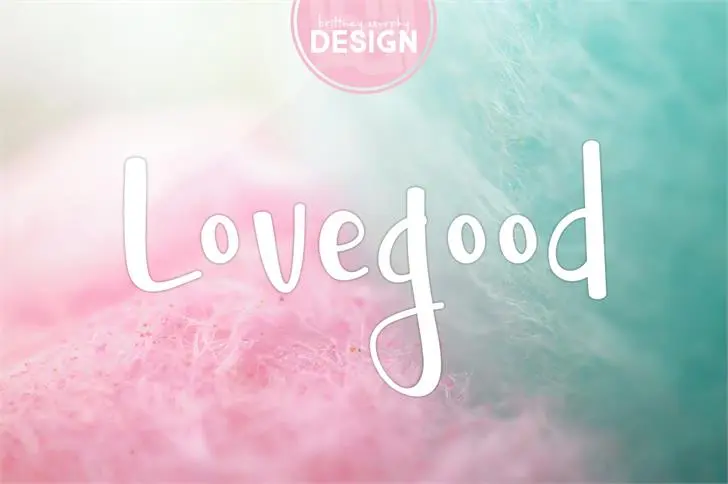
Lovegood Font – Download Grátis
Aqui está uma descrição para a página de download da font ‘Lovegood Font’, adaptada ao tom solicitado: A font ‘Lovegood’ é uma opção ideal para quem busca algo fresco e descontraído no seu design gráfico. Trata-se de um script elegante, desenhado à mão livre, que exibe personalidade e criatividade sem restrições! É perfeito para criar logomarcas divertidas e headlines impactantes. Perfeita para qualquer projeto pessoal ou hobby, esta font é uma ótima opção. Porém, se você deseja integrá-la em projetos comerciais, não hesite em adquirir um licenciamento através do link disponível: https://goo.gl/waAMiE. Com sua versatilidade e estilo único, ‘Lovegood’ certamente encaixará perfeitamente no seu trabalho!